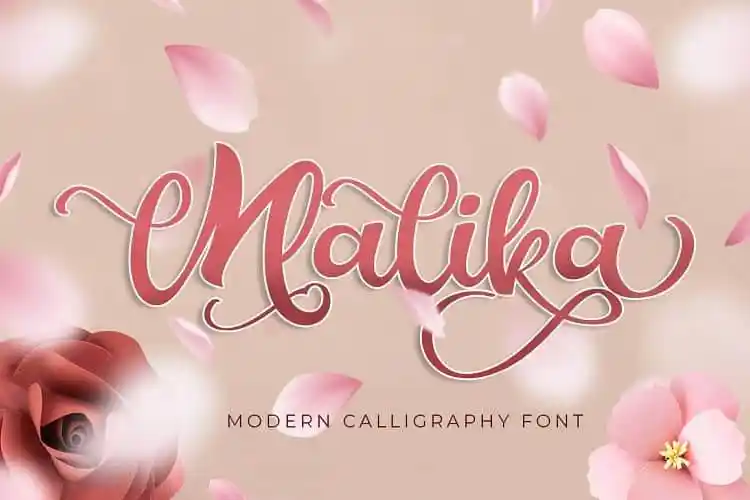
Malika Script Font – Download Grátis
A Malika Script Font é uma elegante escolha para aqueles que buscam uma fonte de estilo calligrafia moderno com traços marcantes. Perfeita para criar designs incrivelmente belos, especialmente ideal para cartas de convite, cartões de cumprimento, materiais de marca, cartão de visitas e até mesmo para anúncios e panfletos. Com seu estilo de escrita, a Malika Script Font se destaca como um recurso indispensável em qualquer projeto que exija uma aparência sofisticada e encantadora. Nela você encontrará a criatividade necessária para destacar seus projetos, seja eletrizante ou refinado. Que tal dar vida a suas criações com o ar de encanto dessa fonte inovadora?